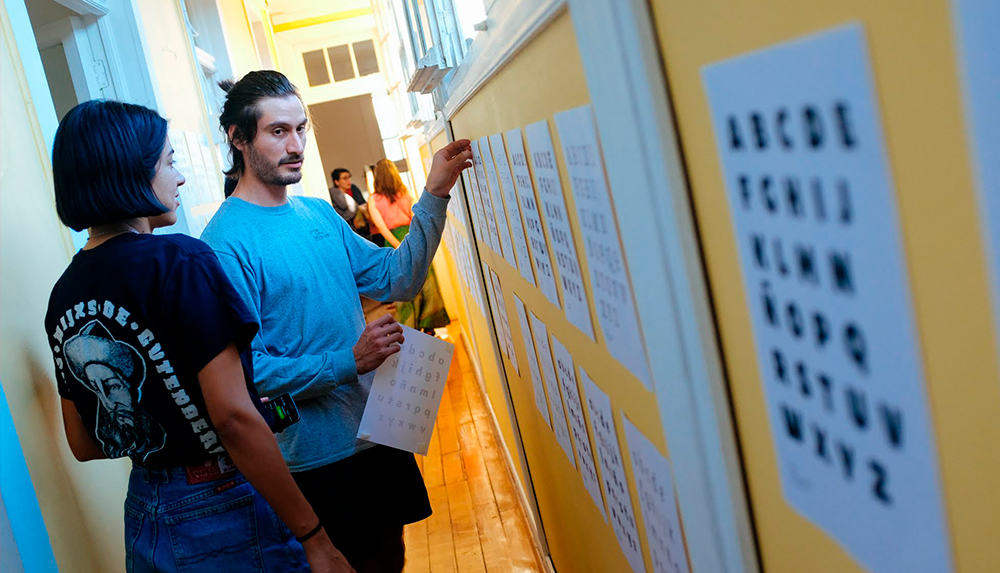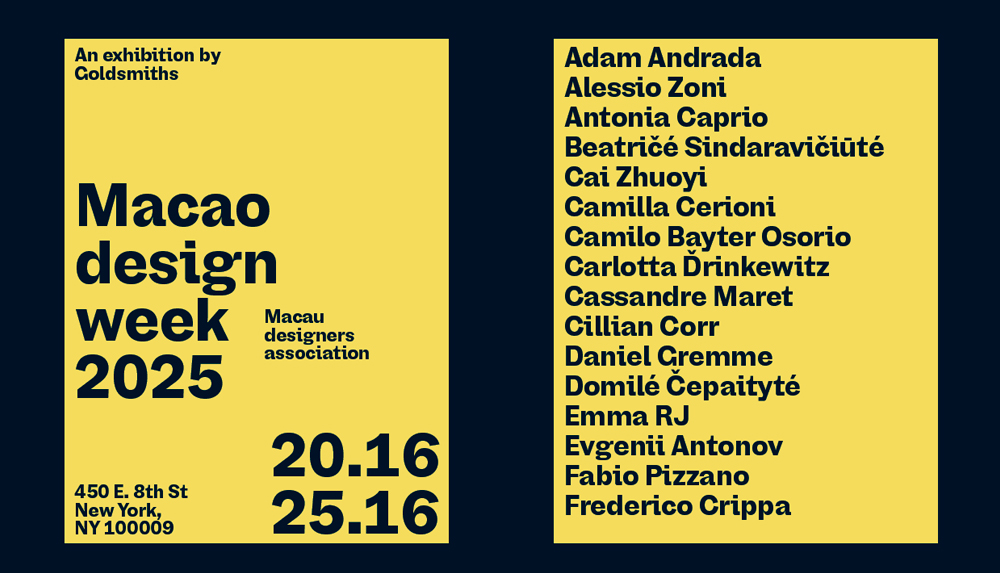
Conversamos con W Type Foundry, equipo de diseñadores tipográficos chilenos que, a pesar de su juventud, cuenta con una rica experiencia que se materializa en un catálogo de fuentes muy variado y profundo.
«Cuando partimos teníamos esa sensación de que había que llegar a un lugar fijo para decir “lo hicimos”, pero ya sabemos que ese lugar no existe y siempre hay que estar moviéndose». Con semejante prueba de sentido común no resulta extraño que W Type Foundry, tras cinco años de experiencia empresarial en el mundo del diseño tipográfico, se haya consolidado como un prestigioso referente del sector en Latinoamérica.
Formado en 2016 por Magdalena «Bana» Arasanz, Diego Aravena, David Súid, Gaspar Muñoz y Patricio Truenos, W Type Foundry se definen a sí mismos como una empresa dedicada a «diseñar tipografías de alta calidad y ser mediadores entre la disciplina de la tipografía y el medio en el que nos desenvolvemos».
los inicios
W Type Foundry surgió de la pasión compartida por la tipografía un poco sin plan preconcebido. Los proyectos más sólidos y duraderos van tomando forma de manera natural.
«Primero nos juntábamos a corregir en nuestras casas, algo super informal. Después pasábamos todo el día, toda la semana, en la casa de Bana. Ahí nos dimos cuenta que ya era un trabajo. Empezamos a cumplir con roles desde el trabajo que a cada uno se le daba de manera orgánica».
«A medida que el proyecto crecía, nos dimos cuenta de que necesitábamos tres aspectos para funcionar de forma óptima y que cumpliera con los intereses del equipo. Los dividimos en tres áreas grandes: organización, articulación y diseño».
cómo hacer rentable la creatividad
No pueden sin embargo evitar una queja sobre la falta de conexión que existe entre la formación académica que se imparte en las escuelas oficiales y la realidad del mundo empresarial, lo que provoca que los recién egresados de las escuelas de diseño no sepan una sola palabra sobre economía de la empresa o cómo montar un negocio que funcione.
«En Chile los diseñadores son educados más como productores de diseño.»
W Type Foundry
«Buscamos taller, postulamos a fondos estatales para armar una empresa, desde ahí no hemos parado. Nos hicimos legales, un paso que no nos enseñan en la escuela de diseño o no incentivan lo suficiente, en Chile los diseñadores son educados más como productores de diseño. Todos nuestros aprendizajes de empresa han sido desde cero».
tipografía y compromiso político
Su catálogo tipográfico es amplio y variado, muy rico en matices y motivaciones, tanto estilísticas como conceptuales, «inspirado en tendencias, investigaciones históricas y formales, y también en motivaciones políticas».
Motivaciones políticas que dan lugar a fuentes tipográficas de protesta como Mercurio Miente y la muy conceptual Variante Piñera, ambas de distribución gratuita. Y un férreo compromiso social a través de la tipografía, que se materializa a través de su constante disposición «a poner nuestras tipos al servicio de la comunidad en proyectos culturales, sociales o sin fines de lucro afines a nuestros principios e ideas, como el respeto, inclusión, educación, movilización social, la historia, comunidad, etc. Desde esta mirada las tipografías creadas son más importantes por su trasfondo colaborativo que su resultado».
Ello unido a una gran actividad de charlas y talleres, truncada por desgracia por la pandemia, a los que suelen invitar «a colegas y otros diseñadores a dar charlas o conversar, todo abierto a quienes quieran ver y participar».
experimentación y comercio
Las otras dos patas, además de la sociopolítica, que soportan todo el andamiaje de motivaciones de W Type Foundry son, por un lado, «diseñar para un mercado amplio orientado al retail, siempre con una propuesta propia en mente y respetando nuestro estándar de calidad. Esto es lo que genera la mayor parte de nuestros ingresos».
Y por otra parte, dedicar «un espacio más abierto a la experimentación donde desarrollamos fuentes más experimentales, de propuesta, con investigaciones históricas o incluso de denuncia como es el caso de Mercurio Miente y Piñera. Para nosotros es importante pasarlo bien en la búsqueda de cosas nuevas, compartir nuestros experimentos o ideas que estamos explorando. Además al operar de esta manera te recargas para poder dedicarle algunas semanas a la sección comercial».
la tipografía más grande del mundo
Maquinaciones experimentales con implicaciones sociales, experiencias de creación tipográfica colectiva. «Estamos planeando la próxima edición del “Collaborative Typography Workshop” para la primera semana de octubre».
«Las ediciones pasadas nos asociamos con el festival New Latin Wave (NY) y con TTBCN (Barcelona). Los resultados de este taller han generado la tipografía colaborativa más grande del mundo, con 172 autores y 37 países hasta ahora».
«El objetivo es diseñar una tipografía de manera colaborativa con múltiples autores, dividiendo letras, números, símbolos y puntuación entre quienes participen para finalmente unir todo en una tipografía funcional y completa. Los participantes construyen una letra asignada recortando formas y pegándolas sobre una grilla».
present is female
«Este año también hemos puesto esfuerzos en priorizar la colaboración con mujeres, sobre todo en nuestro rubro, donde los hombres generalmente son más protagonistas. Creemos que es necesario empujar políticas de paridad en nuestra propia empresa».
«Esto es parte de nuestra postura como grupo incluyendo una mujer a la cabeza. Nuestro objetivo este año es que al menos la mitad de nuestrxs colaboradoxs externos sean mujeres y lograr la paridad. Creemos que es importante dejar esto en evidencia, hablar y exponer este pensamiento».